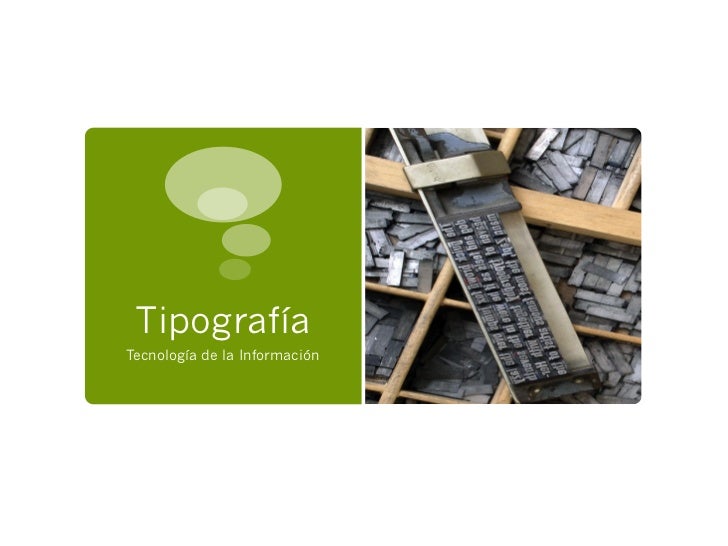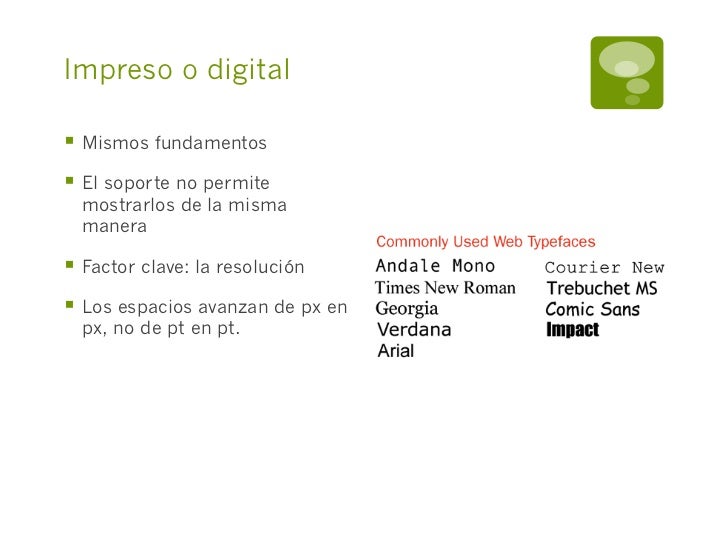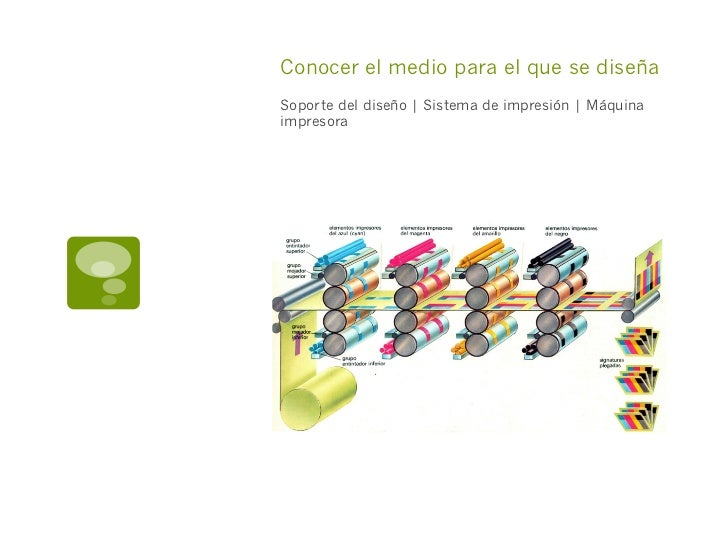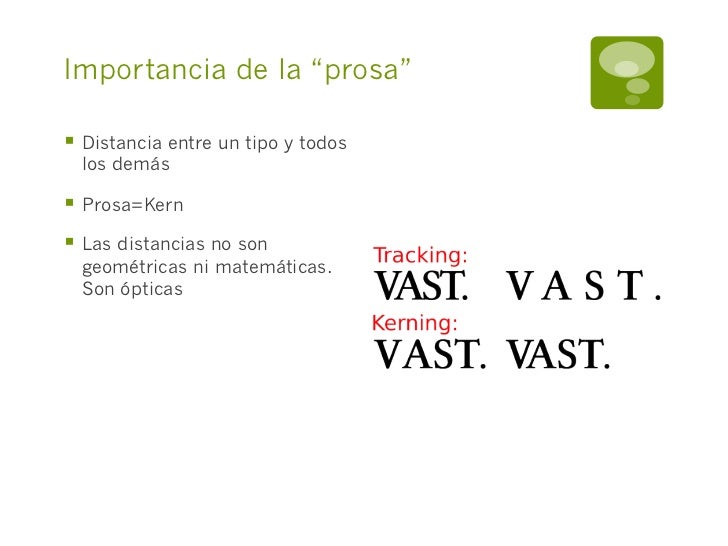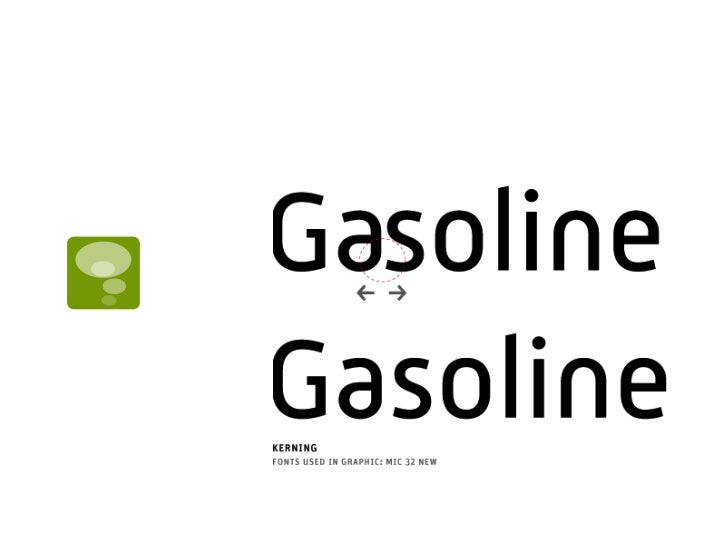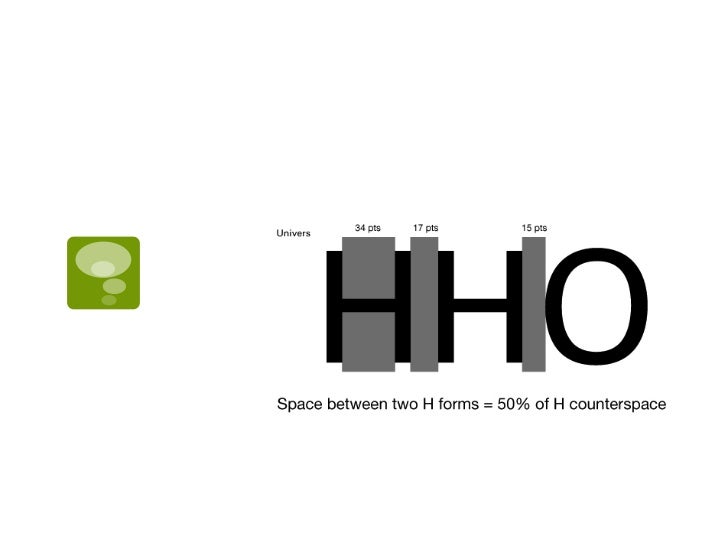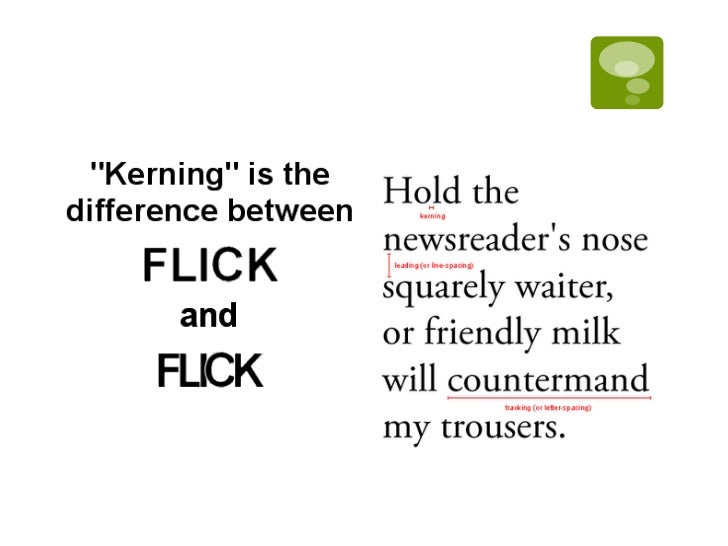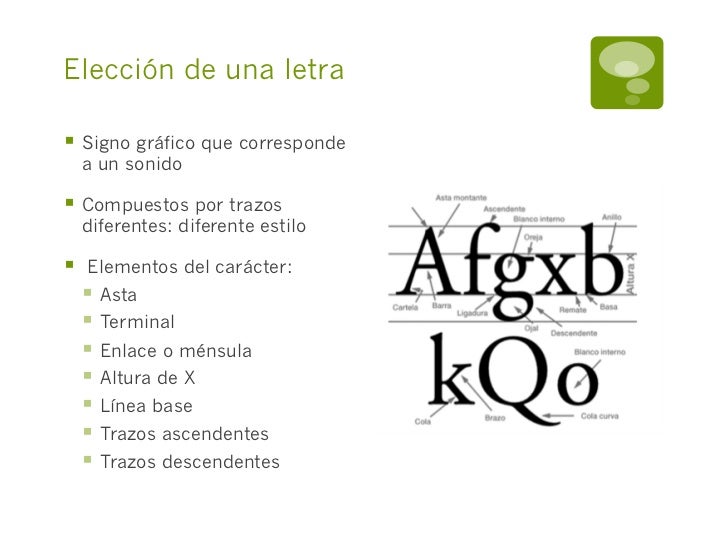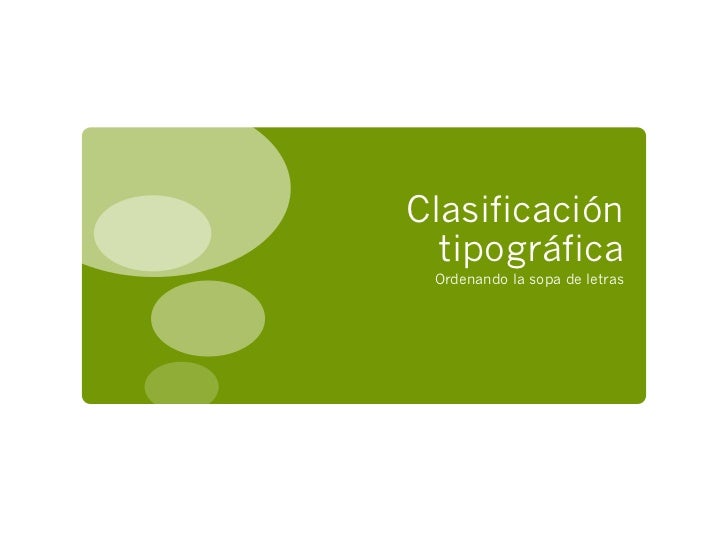
Concepto, tipos y uso de la tipografía
Concepto y uso de la tipografía en diseño y maquetación.
Concepto, tipos y uso de la tipografía
1. 1. TipografíaTecnología de la Información
2. 2. Elección de una letra§  Signo gráfico que corresponde a un sonido§  Compuestos por trazos diferentes: diferente estilo§  Elementos del carácter: §  Asta §  Terminal §  Enlace o ménsula §  Altura de X §  Línea base §  Trazos ascendentes §  Trazos descendentes
3. 3. Elección de una letra§  Todas las líneas de texto se delimitan por cuatro líneas guía invisibles:§  Línea base§  Línea de altura de X§  Línea de trazos ascendentes§  Línea de trazos descendentes
4. 4. Seleccionando la legibilidad
5. 5. Legibilidad Vs. Visibilidad
6. 6. Interlineado e interletrado
7. 7. La modulación
8. 8. La modulación Oblicua Vertical
9. 9. HumanaMaximilien VoxGaraldaMaximilien VoxRealMaximilien Vox
10. 10. Impreso o digital§  Mismos fundamentos§  El soporte no permite mostrarlos de la misma manera§  Factor clave: la resolución§  Los espacios avanzan de px en px, no de pt en pt.
11. 11. Impreso o digital.Recomendaciones§  Fuentes diseñadas para pantalla§  Fuentes incluidas en el sistema del lector§  Fuentes de un tamaño mayor que en medios impresos§  Tipos de ojo grande. Poca diferencia entre tipos con remate y sin remate§  Invertir tipos en títulos y textos§  Usar la versión regular
12. 12. Conocer el medio para el que se diseñaSoporte del diseño | Sistema de impresión | Máquinaimpresora
13. 13. Importancia de la “prosa”§  Distancia entre un tipo y todos los demás§  Prosa=Kern§  Las distancias no son geométricas ni matemáticas. Son ópticas
14. 14. Terminología básica§  Carácter y familia tipográfica§  Contraste§  Enlace§  Fuente§  Modulación§  Ojo§  Remate§  Visibilidad y legibilidad
15. 15. Enlace o ménsula M M Vs.
16. 16. Clasificación tipográfica Ordenando la sopa de letras
17. 17. §  Conocer y valorar las diferentes familias aumenta la calidad§  Motivos de la clasificación §  Los diseñadores pueden elegir según características comunes §  Permite catalogación histórica
18. 18. Sistemas de clasificación§  Thibaudeau. 1921 §  Romanas §  Antiguas §  Modernas §  Egipcias §  De palo seco §  Escritura o góticas §  Fantasía§  Maximiliano Vox. 1953§  Giusepe Pelliteri. 1963§  Perfect
19. 19. Clasificación de Alex BrownAutoedición. Texto y tipografía en la era de la ediciónelectrónica (1992)
20. 20. §  Caracteres con remate §  Caracteres de palo seco §  Antiguas §  Sin modulación §  Caligráficas §  Con modulación §  Remates suaves §  Caracteres rotulados §  Remates afilados §  Caligráficos §  Remates gruesos §  Góticos §  De transición §  De escritura §  Modernas §  Cursivos §  Normandas §  Egipcias §  Caracteres decorativos §  Con remates cuadrados §  De fantasía §  De época
21. 21. Con remate antiguas
22. 22. Con remate caligráficas
23. 23. Con remate suaves
24. 24. Con remate afilados
25. 25. Con remates gruesos
26. 26. De transición
27. 27. Modernas
28. 28. Normandas
29. 29. Egipcias
30. 30. Con remates cuadrados
31. 31. De palo seco sin modulación
32. 32. De palo seco con modulación
33. 33. Rotulada caligráfica
34. 34. Rotulada gótica
35. 35. Rotuladas de escritura
36. 36. Rotuladas cursivas
37. 37. Decorativas de época
38. 38. Decorativas de fantasía
39. 39. Un tipo para cada contenido Tipos de titular y de texto
40. 40. §  Los tipos se miden en puntos Didot. §  Unidad de medida duodecimal. §  Firmin Didot. Finales del XVIII.§  Tipos de titular: más de 14 puntos.§  Tipos de texto: menos de 14 puntos (8–12).
41. 41. Tipos adecuados para textos§  Mirar tamaño y estilo.§  Entre 7 y 8 antiguamente.§  8 ó 9 con un punto más de interlineado en la actualidad.§  Recomendaciones §  Caracteres con remate §  Si es sin remate un punto más de interlineado §  Grosor medio. Ni supernegra ni extrafina §  Ni cursiva ni negrita. Regular.
42. 42. Tipos adecuados para títulos§  Textos a más de 14 puntos.§  El estilo de los títulos marca el estilo del medio.§  Aspectos a considerar: §  Fuerza o mancha. §  Cuerpo o tamaño. §  Anchura. §  Colocación.
44. 44. Tipos adecuados para títulosReverse kicker EJEMPLO de reverse kicker
45. 45. Tipos adecuados para títulos Wicket Este es unejemplo de WICKET
46. 46. Tipos adecuados para títulos TrípodeTRÍPODE Este es su ejemplo
47. 47. Tipos adecuados para títulosTrípode Esta esotra opción de titular
48. 48. Tipos adecuados para títulosTrípode Un titular puede ir perfectamente dividiendo una entradilla general cuando de lo que se trata es de titular presentar un reportaje de varias páginas. Es una forma un tanto arrevistada que se da en magazines.